逆反差字体(Reverse Contrast)最早可以追溯到19世纪,主要的用途是利用逆反差效果所造成的奇异性格(Quirky Personality)来引起注意力。
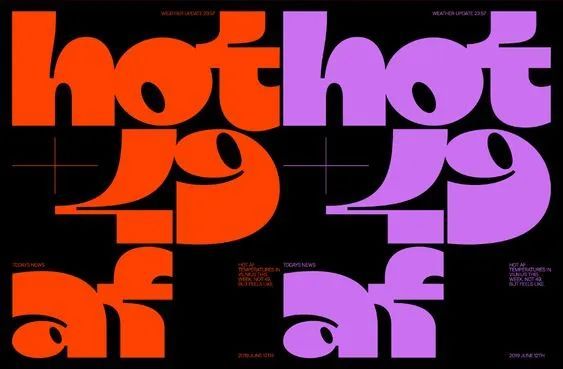
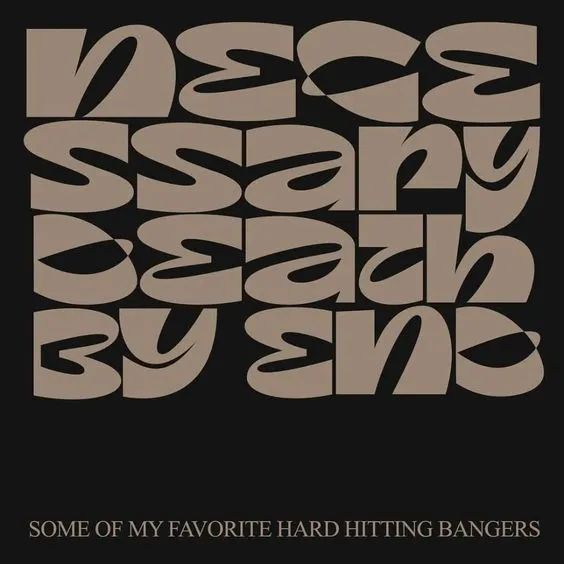
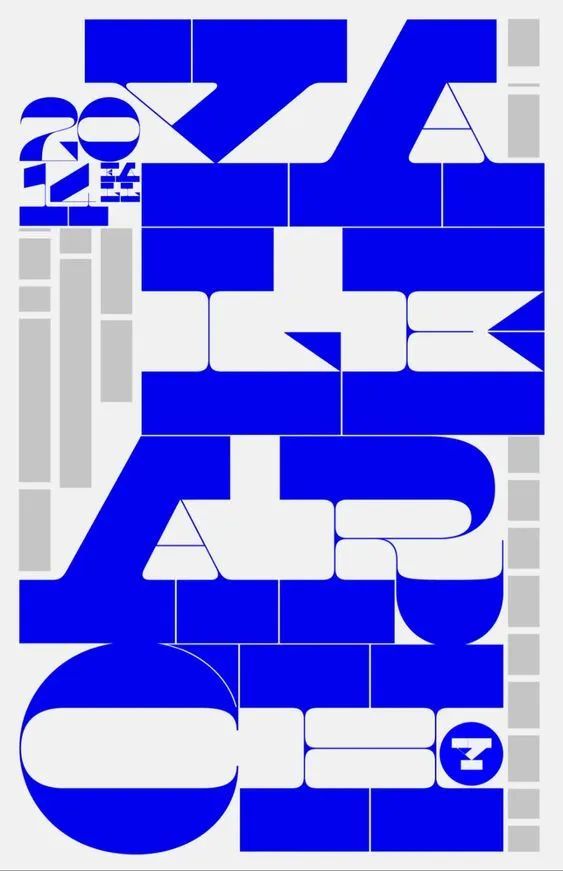
中文逆反差字体中比较著名的当属现居纽约的华人设计师廖恬敏(Tien-Min Liao),她的作品获得了Type Directors Club、Tokyo TDC和Morisawa Type Design Competition的认可。
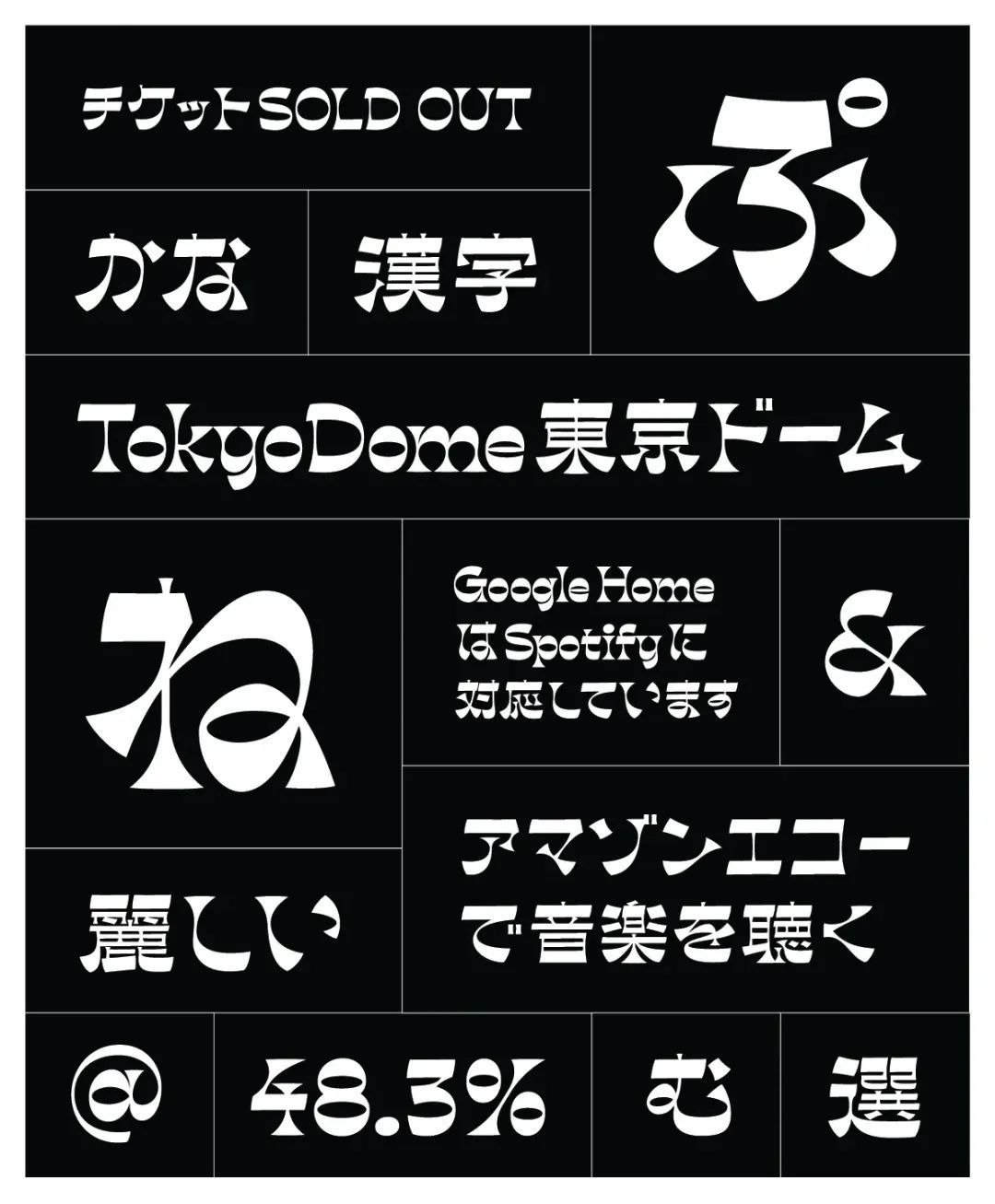
它的特色是有着强烈的横向连结感及一致性,笔画的重量也恒定地分布在上中下三区。逆反差字体在汉字或假名设计中本来不存在,它是拉丁文字特有的结构所延伸出来的一种设计规则。
拉丁文字大致上粗细分布保持一致:横细竖粗。除了弧形笔画,很少有粗细变化极端的单一笔画。在这样单纯的结构中,把原先粗笔画逆反成细;细笔画逆反成粗,就成为逆反差字体。
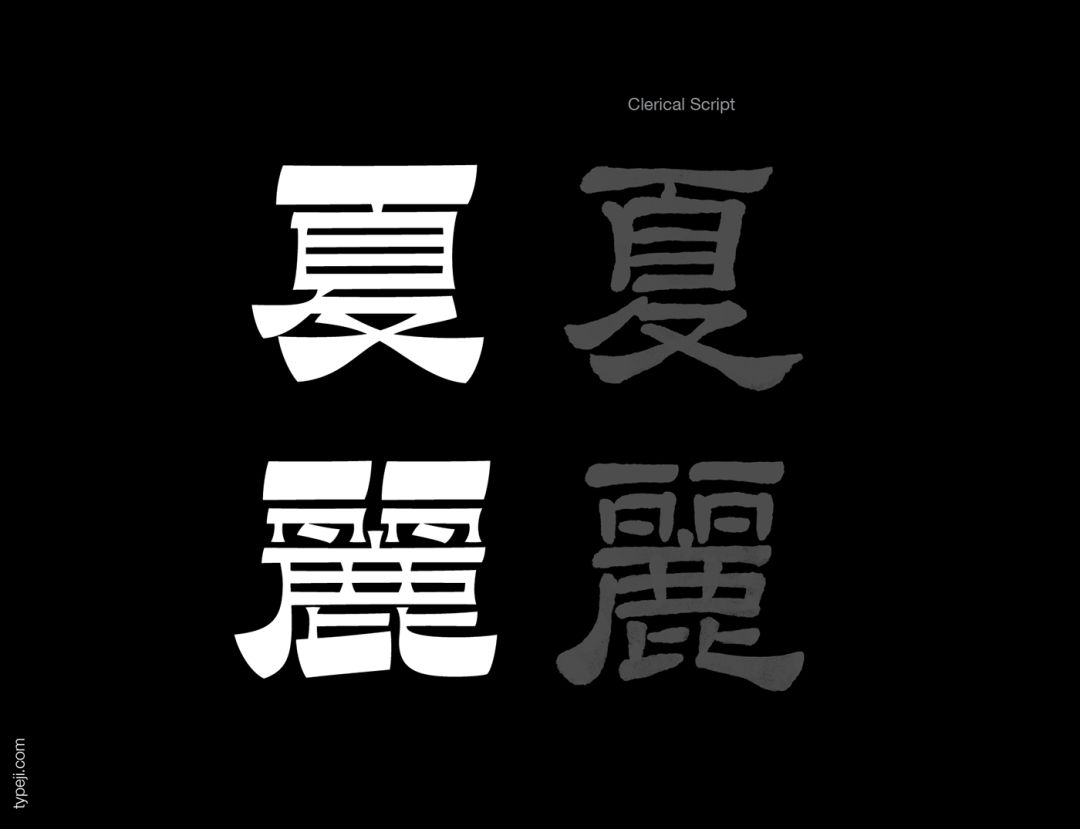
汉字或假名的设计与欧文不同,他们的粗细分布是根据书法传统而来。文字本身的结构变化复杂,如果直接以「逆反差」字面本身的意思来绘制汉字,反而难以达到逆反差字体独有的特色。既然逆反差字体是拉丁文字设计所延伸出来的概念, 设计对应的汉字或假名时,或许可从欧文逆反差字体的视觉结果来做分析,抓住逆反差字体给观者的视觉感受与特色:1.强烈的横向连结、2. 恒定的重量分布,以及 3.逆反差所造成的奇异性格。而Ribaasu是以前述三项要点为前提,所提出的一种字体设计方案。
廖恬敏设计的这套「Ribaasu Typeface」还获得了纽约字体俱乐部评审特选奖、日本森泽字体竞赛铜赏及入选东京TDC。
廖恬敏的这套逆反差字体更偏向书写的特点,另一种设计逆反差字体的思路是用几何化的形式语言去设计,我们来看一些例子:
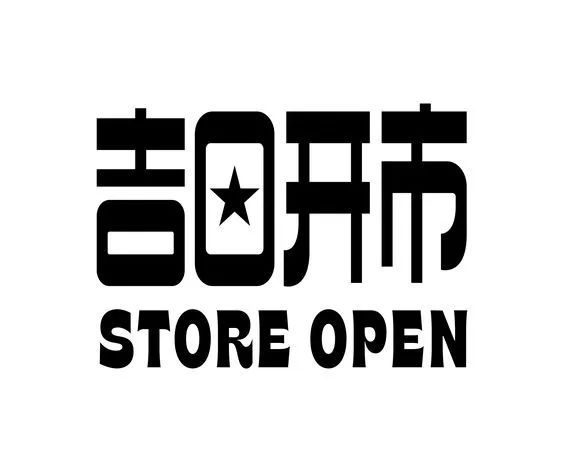
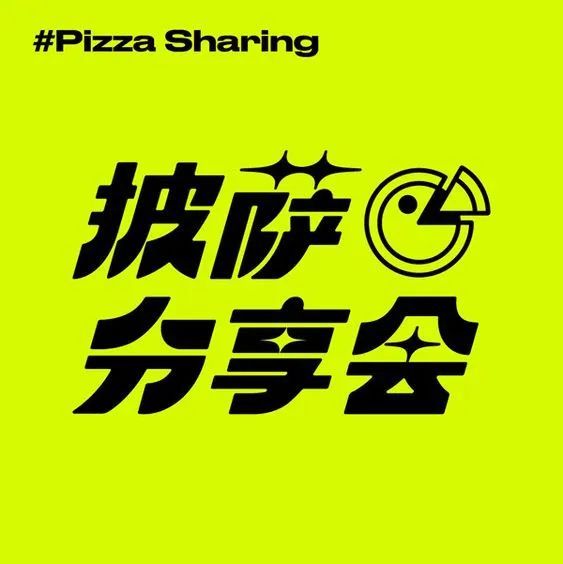
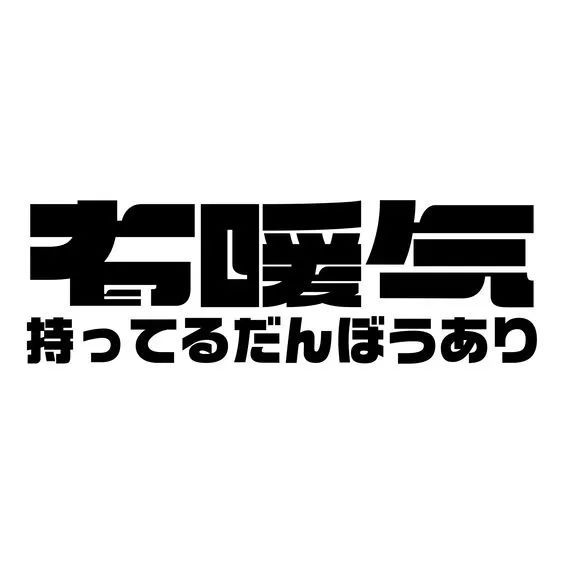
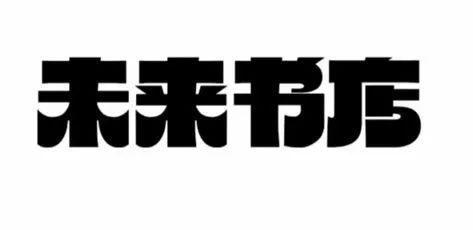
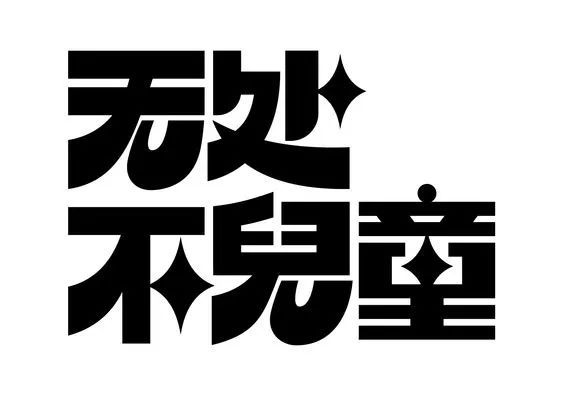
这种风格的字体,我也设计过一些,前段时间在站酷发表的字体合集中有过展现: